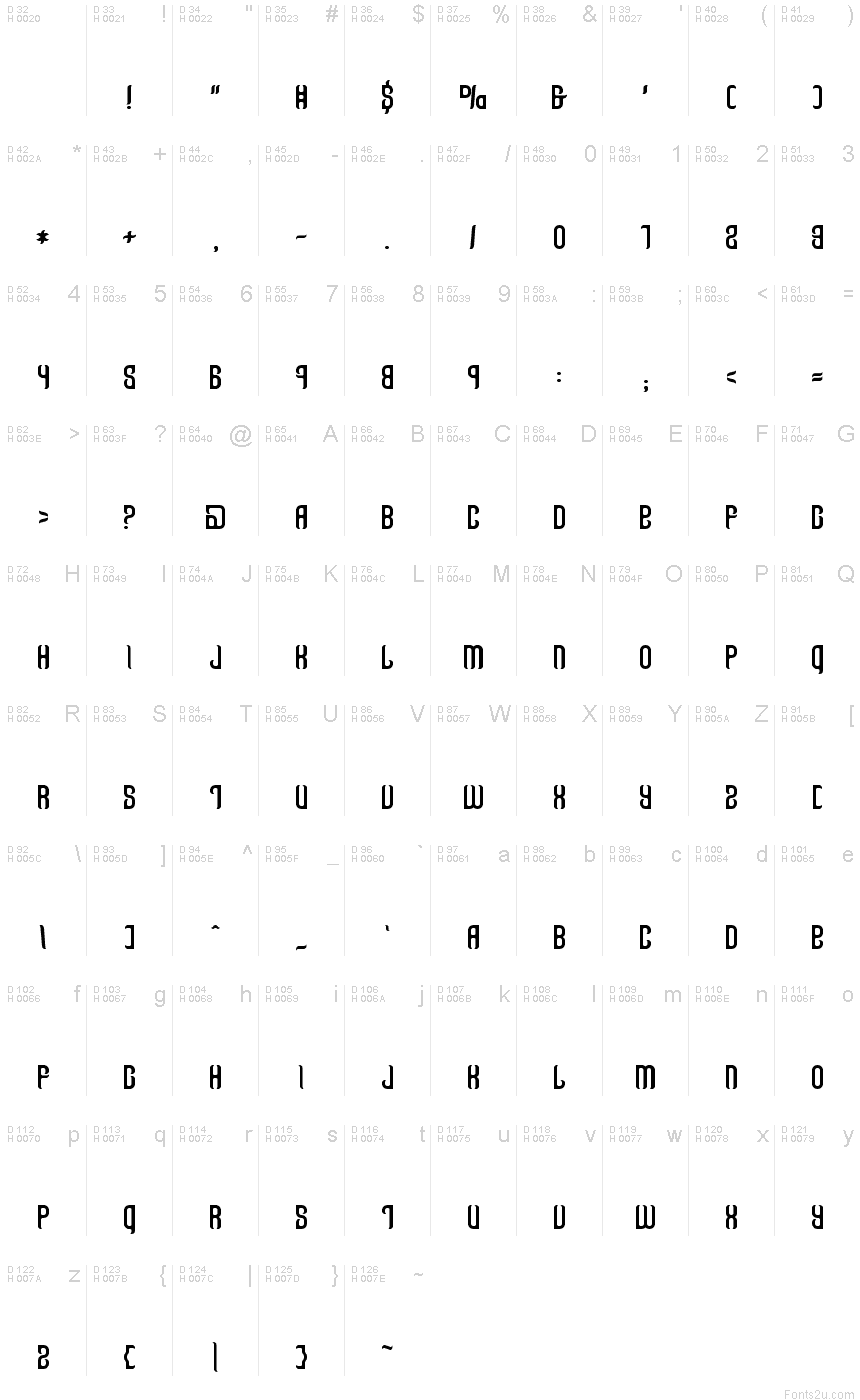
Talismanica
Talismanica autorstwa Claesa Kallarssona to darmowy, groovowy krój displayowy z klimatem plakatów z późnych lat 60. Litery łączą w sobie wyrazistą, pionową konstrukcję z miękkimi, wypukłymi krzywiznami i głębokimi wcięciami. Dzięki temu krój jest zarówno dekoracyjny, jak i płynny – nie sprawia wrażenia sztywnego – a jego lekko psychodeliczny rytm powtarza się w każdym znaku.
Idealnie pasuje do plakatów muzycznych, opakowań butikowych, ulotek klubowych, nagłówków w magazynach czy retro plansz tytułowych, gdzie odrobina dramatyzmu pomaga słowom „udźwignąć” cały projekt. Jako darmowy font, Talismanica sprawdza się również w krótkim brandingu, monogramach i przyciągających wzrok tytułach, zwłaszcza gdy szukasz tej „topiącej się” sylwetki w stylu lounge, a nie surowego, nowoczesnego kroju.